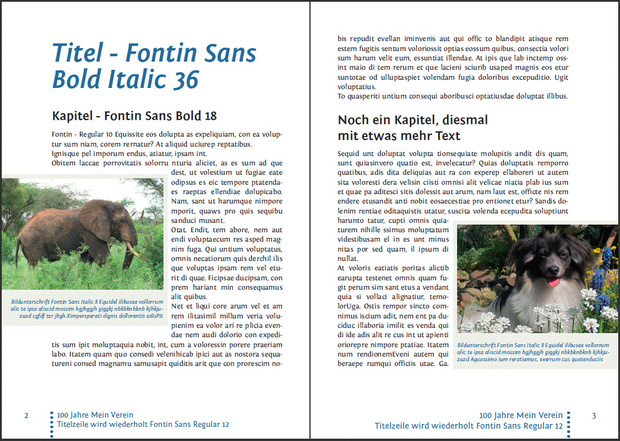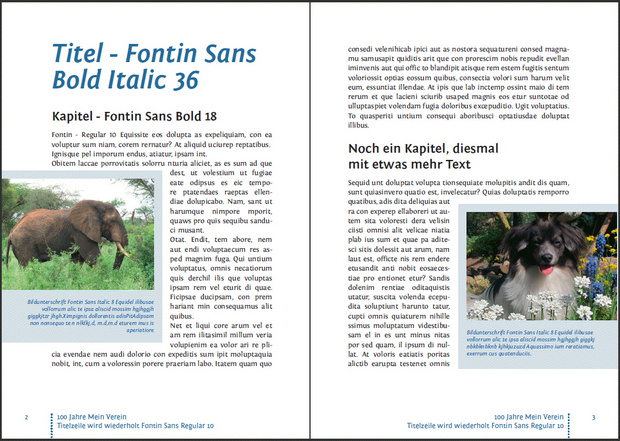
Satzspiegel und Schriftarten für Festschrift zum Vereinsjubiläum
Wie gesagt, die Minion kannst Du so mischen wie die Times. Was auch gut passt sind z.B. Myriad (auch von Slimbach entworfen, ebenfalls einige Schnitte beim Reader dabei) und Scala Sans (Bringhurst verwendet die so in seinem Buch).
Ich würde keine drei Schriften in einem Buch verwenden, wenn es nicht absolut zwingend notwendig ist. Die Bildunterschriften sind ohnehin kleiner als der Fließtext, und dann entweder in der Fließtextschrift oder in der zweiten Schrift :)
Was zur Minion passt, ist (ja, die Suche hier funktioniert!) ein überaus unerschöpfliches Thema. Sehr spannend und sehr lesenswert, ich empfehle einfach mal etwas zu stöbern. Das soll aber bitte nicht davon abhalten weiter Fragen zu stellen, so war das nämlich nicht gemeint.
1. Schrift
Die Minion ist, mit Verlaub, genauso abgelutscht wie die Optima. Erstere mag wegen ihres konservativen Aussehens nur nicht so augenfällig. Ich würde von beiden abraten (wie von allen weitverbreiteten Systemschriften im Print). Noch dazu, da Cebolina ja ausdrücklich keine 08/15-Schriften sucht.
Es gibt doch so viele tolle Schriften, die durchaus für den Mengensatz geeignet sind. Wie wäre es z.B. mit:
2. Ränder
Bei DIN A5 wird als Außenrand für derartige Publikationen (es wird ja kein Buch, sondern eine Festschrift mit vermutlich vielen außertextlichen Elementen) häufig ein Rand von ca. 15mm verwendet. Nach dem Vorschlag von Minimalist wäre der Innenrand dann ca. 7,5mm breit, was aber ist viel zu schmal ist. Selbst 10mm für den Innenrand halte ich noch für relativ knapp.
Probiere doch mal einen Rand oben und außen von 15mm, im Bund 12,5mm und unten ruhig etwas mehr als 15 mm. Ich würde das ganze bei der Größe auch nur einspaltig setzen. Dann mach mit der Schrift Deiner Wahl einen Probesatz (Schriftgröße 10–11pt, Zeilenabstand z.B. 5mm), drucke diesen aus (wichtig!) und taste Dich anhand des Ausdrucks an eine für Dich passende Lösung. Vielleicht gefällt Dir ja ein asymmetrischer Satz mit wesentlich größeren Rändern noch besser?
Noch zwei Tipps:
1. Ich würde keinen Blocksatz verwenden. Ein Flattersatz schaut meist lockerer, humanistischer aus. Einen gelungenen Satz in Blocksatz bekommen selbst Profis bei vielen außertextlichen Elementen (wiel Fotos, Grafiken etc.) nicht so schnell hin.
2. Und solltest Du mit dem Umfang nicht hinkommen und Du mehr Text auf die Seiten unterbringen müssen, unterschneide bitte nicht die Schrift, modifiziere sie nicht in der Breite und verringere nicht den Zeilenabstand. Lieber mit dem Schriftgrad etwas kleiner werden und die Ränder anpassen. Alles andere geht auf Kosten der Lesbarkeit (und wer will das schon?).
Ich sehe am Wochenende viel Arbeit auf mich zukommen.
Ich werde mal symmetrische und asymmetrische Satzspiegel ausprobieren und versuchen eure Tipps umzusetzen.
So, da bin ich wieder.
Ich habe übers Wochenende viel ausprobiert und hier mein Ergebnis:
Ränder
oben: 19mm
innen: 13mm
außen: 24mm
unten: 34mm
Schriftart
Titel: Fontin Sans Bold Italic 36
Kapitel: Fontin Sans Bold 18
Fließtext: Fontin Regular 10
Fußzeile: Fontin Sans Regular 12
Ich habe mich für einen (fast) symmetrischen Satzspiegel entschieden.
Der Fließtext wird wohl im Blocksatz gesetzt.
Mir gefällts ganz gut.
Was haltet ihr davon? (Ich hoffe, dass ich mir jetzt nicht das "typografische Fegefeuer" über mich ergehen lassen muss;-))
hm, hast du unsere Beiträge gelesen? Den Innenrand würde ich bei 100–130 Seiten und Klebebindung immer so groß machen, dass beide Innenränder zusammen im zu 2/3 aufgeschlagenen Zustand dem Außenrand entsprechen. Wenn du innen insgesamt 26 mm, außen 24 mm hast, entsteht ein optisches Ungleichgewicht. Mal ganz abgesehen davon dass es sehr mühsam ist, den innen eingeklemmten Text zu lesen.
@bertl
Du meinst also, den Innenrand zu erweitern? Vielleicht auf 15mm.
Die zwischenzeitlichen Einwände von bertl (Größe der Überschrift und Einrückung von Absätzen), sowie von Schnitzel (Seitenzahl) habe ich momentan noch nicht berücksichtigt. Wie bertl und Sebstian schon sagen, muss ich mal echte Texte abwarten und dann sehen, wie ich zurecht komme.
Hier der aktuelle Stand:
Korrektur: "rechter Rand" muss richtig "innerer Rand" heißen